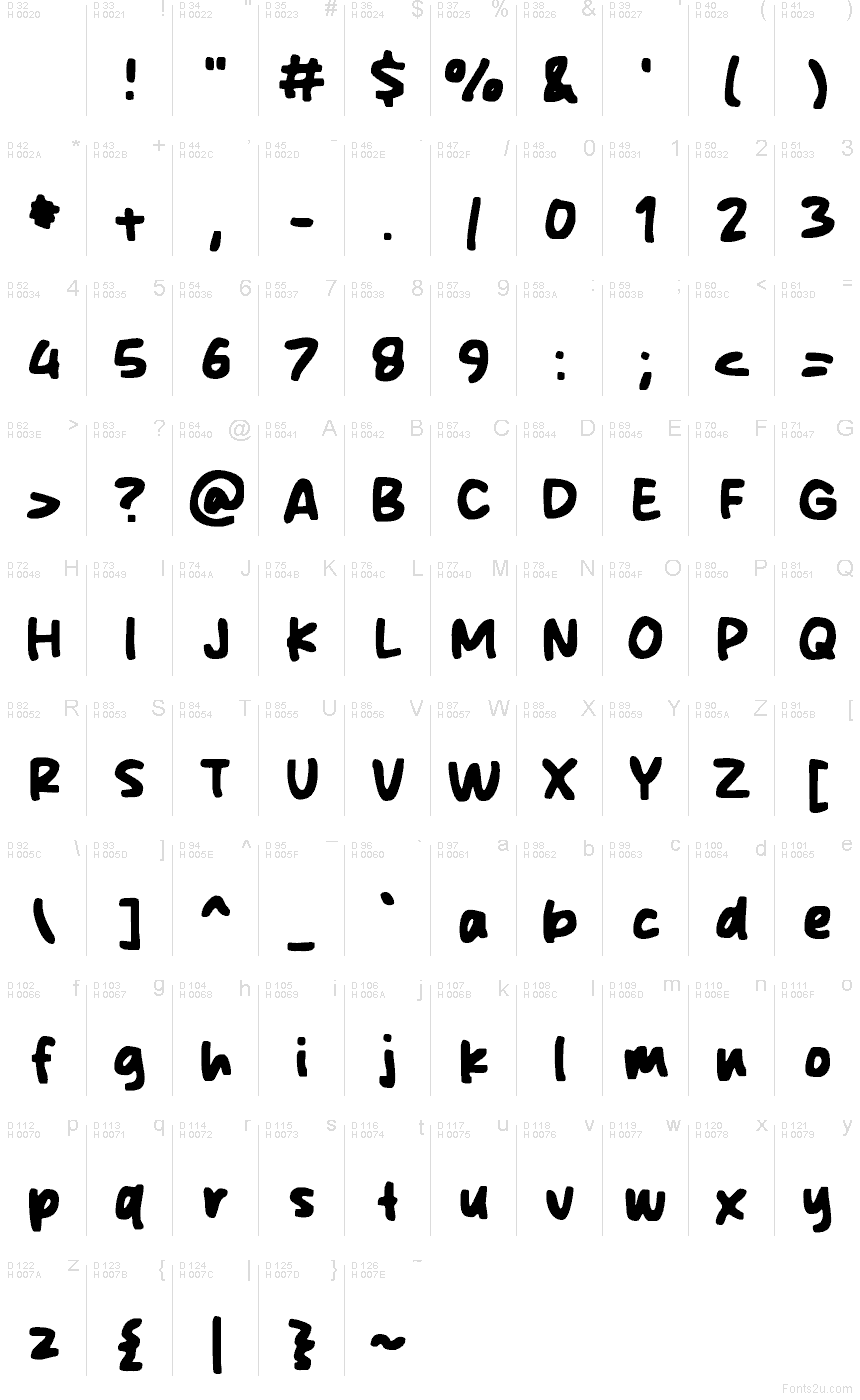
Spidol Clash
Spidol Clash von Origin Type ist eine kostenlose, abgerundete Brush-Schrift mit einem kräftigen, tintenreichen Charakter. Die Buchstaben wirken weich und handgemalt statt glatt poliert; mit ihren bauchigen Kurven, gedrungenen Proportionen und einem verspielten Schwung wirkt die gesamte Wortmarke ungezwungen und ein wenig frech.
Sie eignet sich hervorragend für jugendliche Markenauftritte, Snack-Verpackungen, Plakatüberschriften, Social-Media-Grafiken und Musik-Cover, bei denen ein markanter, aber nicht zu strenger Look gefragt ist. Als kostenlose Schrift bietet sie sich zudem ideal für Titelkarten, Logo-Entwürfe und plakative Zitate an, da die dicken Pinselformen und die klecksigen Verbindungen die Aufmerksamkeit perfekt auf den Inhalt lenken.